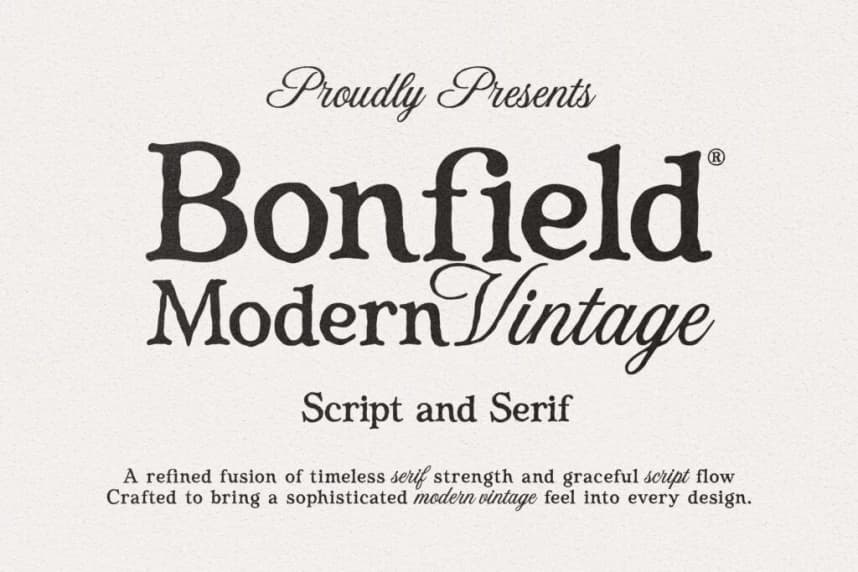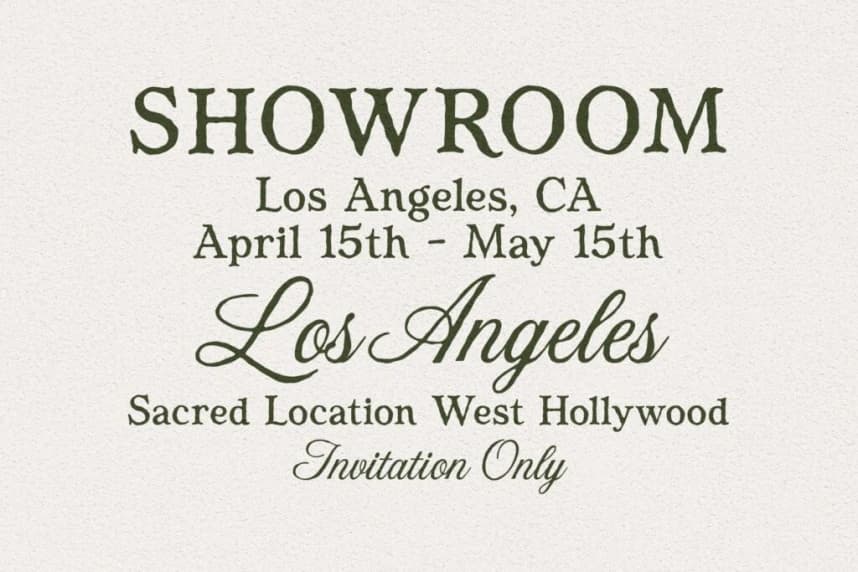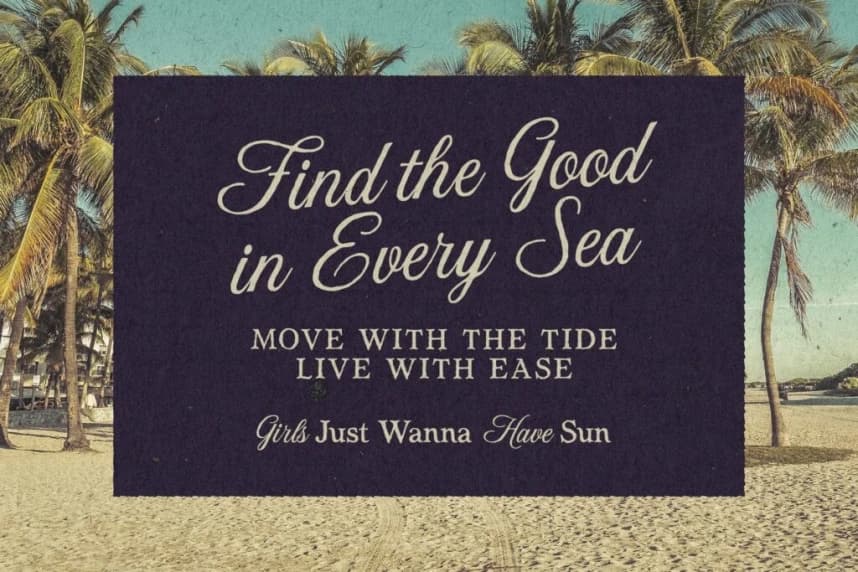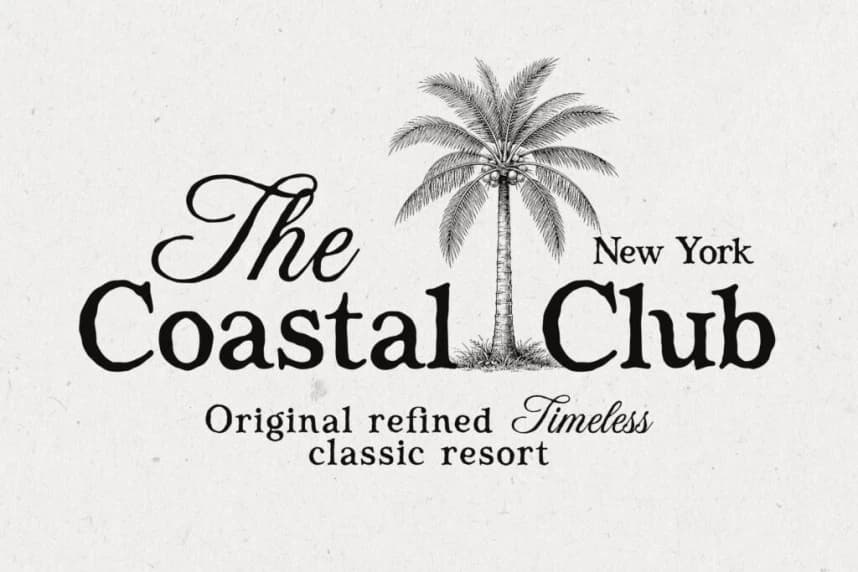
Bonfield Font Duo
Bonfield Font Duo, klasik serif yapısıyla ifade dolu bir script akışını zarifçe birleştiren, yaratıcı projelerinize zamansız ama modern bir vintage estetik katmak üzere tasarlanmış bir font çiftidir. Bu benzersiz yazı tipi, serif'in gücü ve okunabilirliğini organik
Bonfield Font Duo, klasik serif yapısı ile ifade gücü yüksek bir kaligrafik akışın zarif bir birleşimidir ve yaratıcı projelerinize zamansız ama modern bir vintage estetik kazandırmak için tasarlandı. Bu benzersiz yazı tipi, serif'in gücü ve okunabilirliğini organik